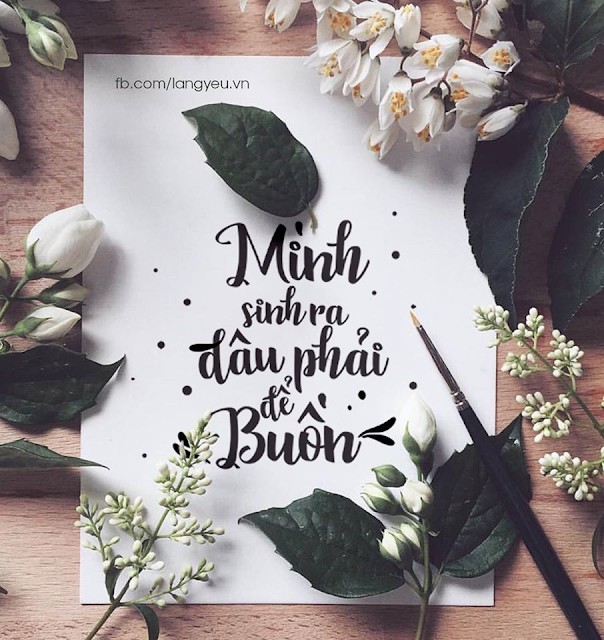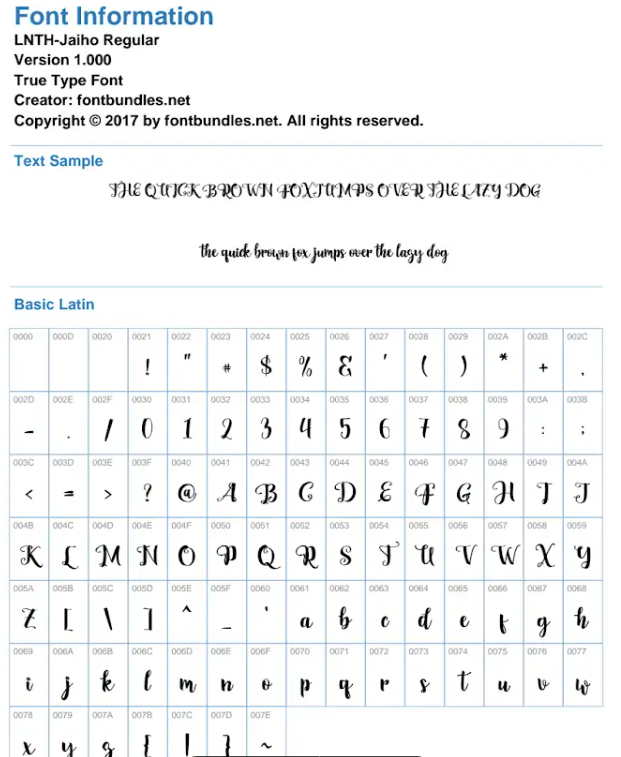
Font LNTH Jaiho Script Việt Hóa
Tác giả: LNTH
Phân loại: Cá tính
Kiểu chữ: Chữ viết tay
Độ dày: Regular
Font LNTH Jaiho Script Việt Hóa là một font chữ nghệ thuật, thuộc bộ LNTH, với thiết kế như nét bút lông. Phong cách của font này phù hợp với các dự án thiết kế cần sự nghệ thuật và sáng tạo, như poster, thiệp mời, hoặc bảng hiệu. Font LNTH Jaiho Script Việt Hóa mang đến sự nghệ thuật và dễ nhận diện, ứng dụng trong các lĩnh vực sáng tạo. Đặc điểm hình dạng của font bao gồm các nét bút lông mềm mại và tự nhiên, giúp tăng tính thẩm mỹ và sự chú ý. Việc Việt hóa font giúp người dùng dễ dàng sử dụng trong các thiết kế tiếng Việt, mang lại sự tiện lợi và linh hoạt.
Font LNTH Jaiho Script